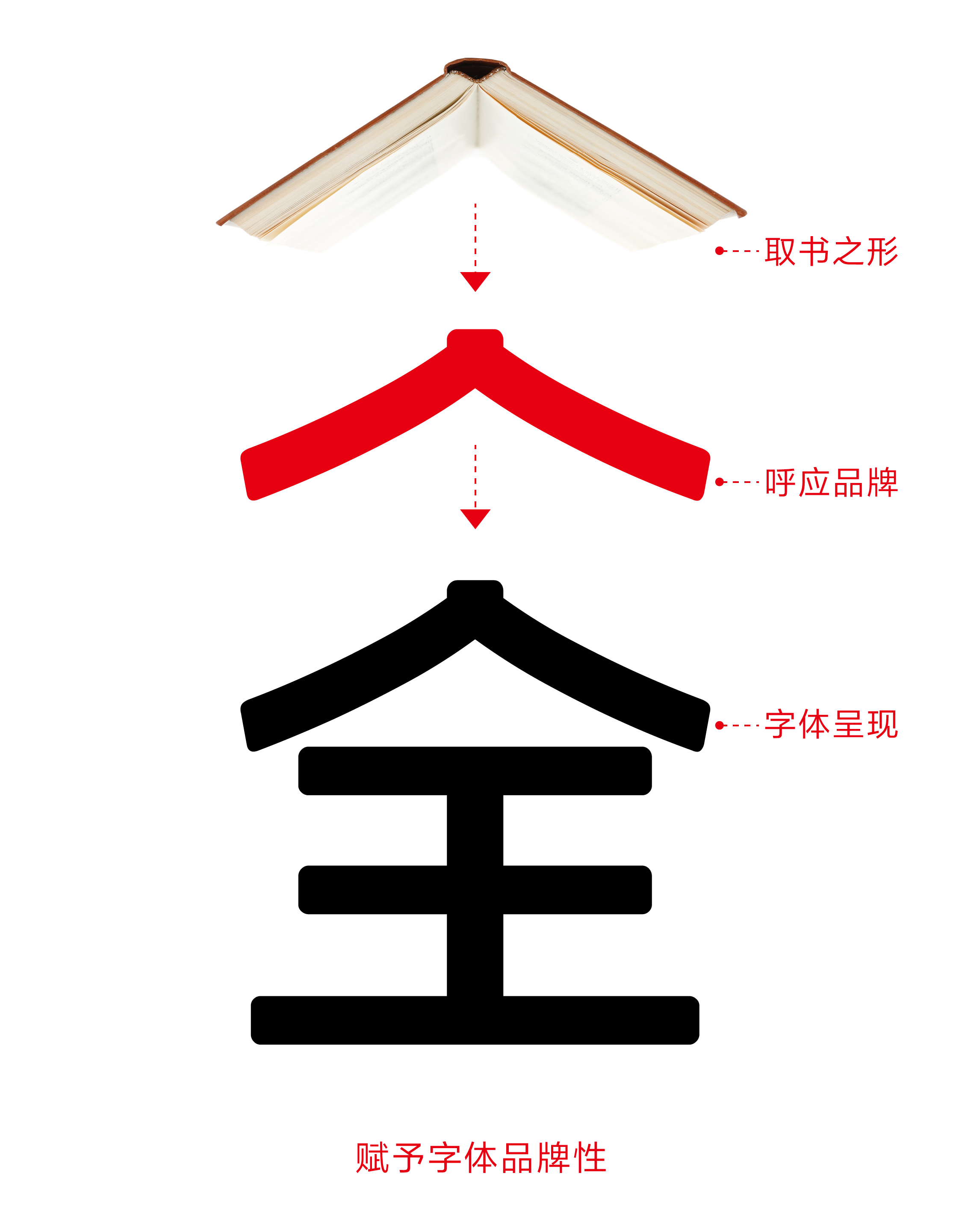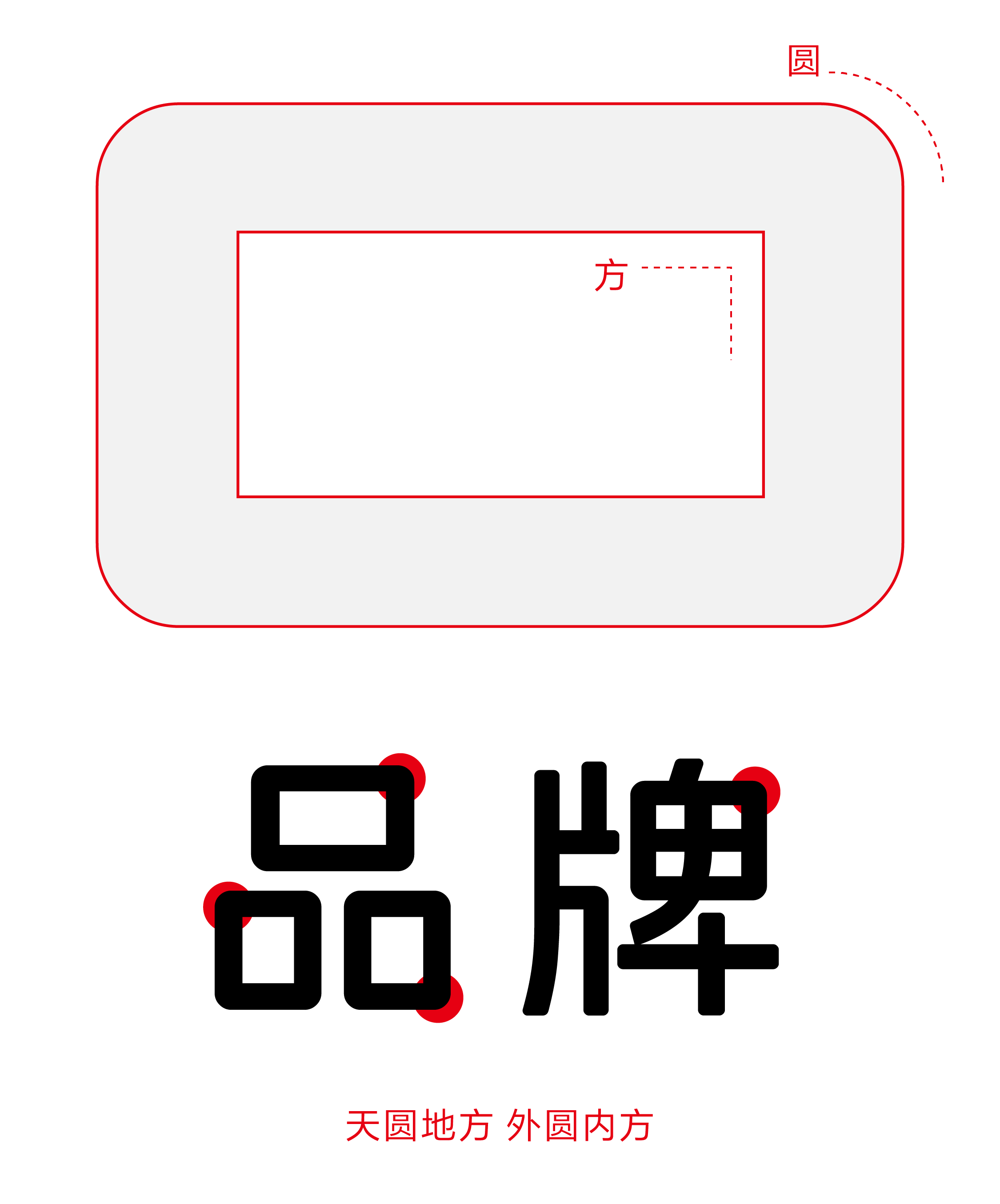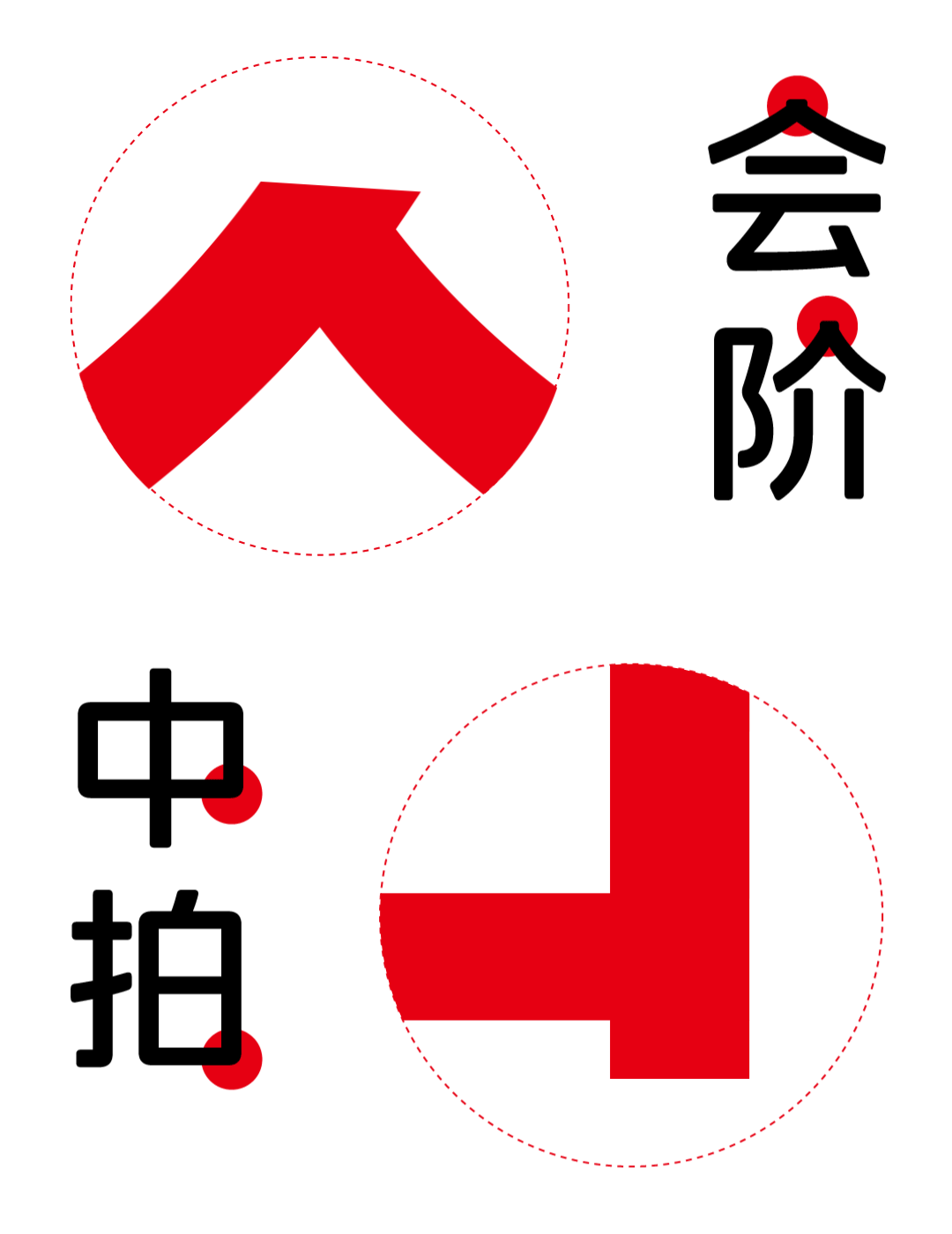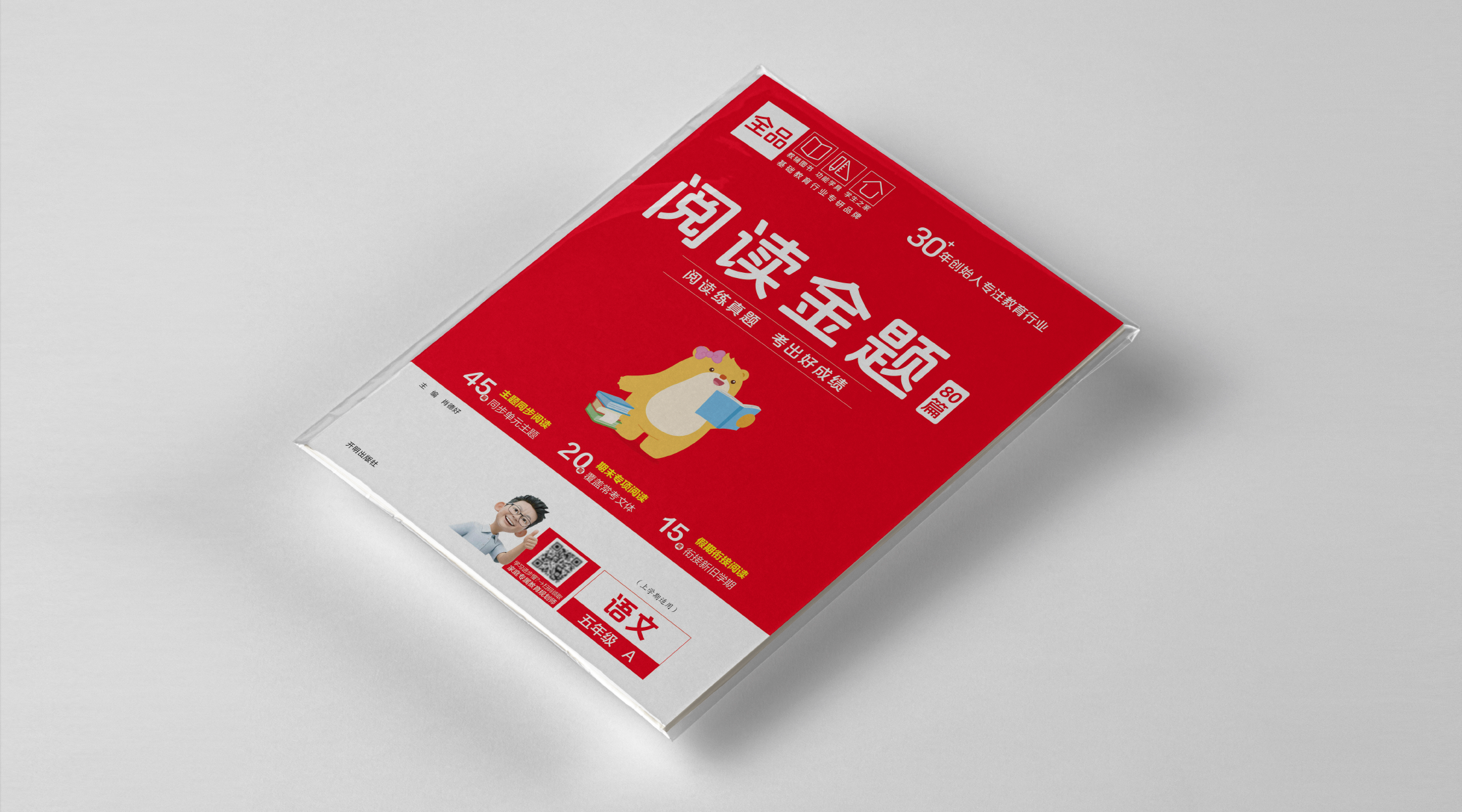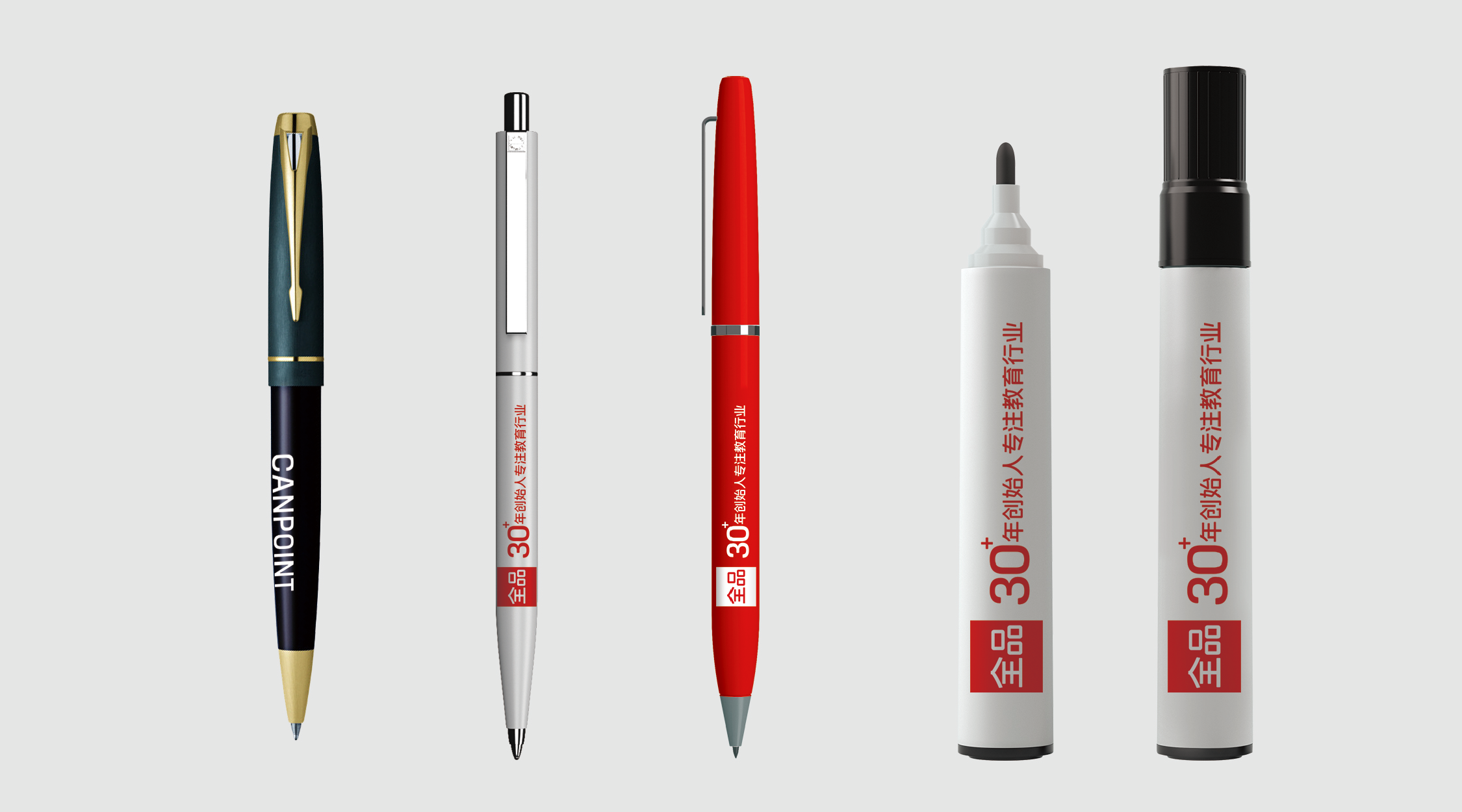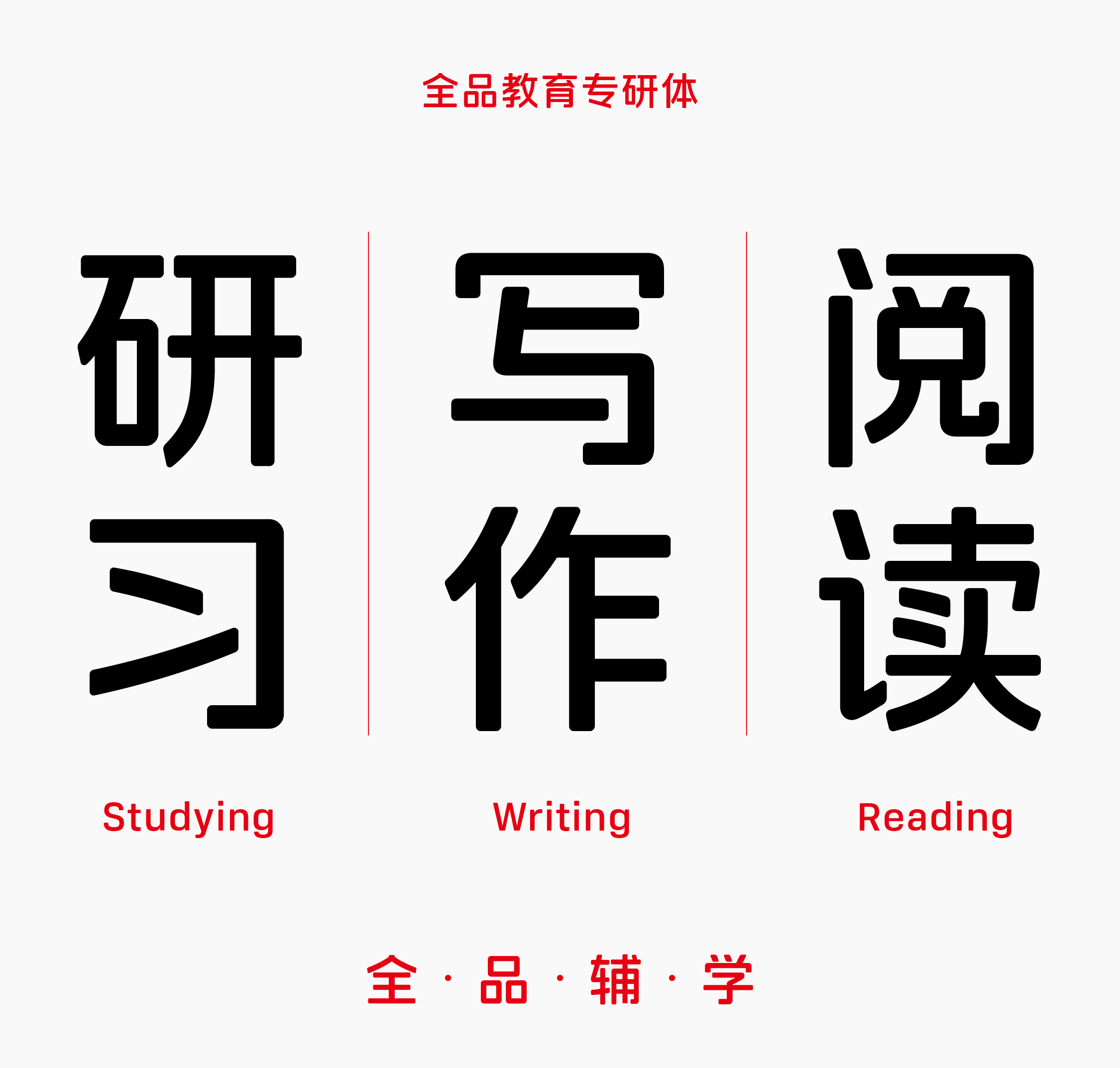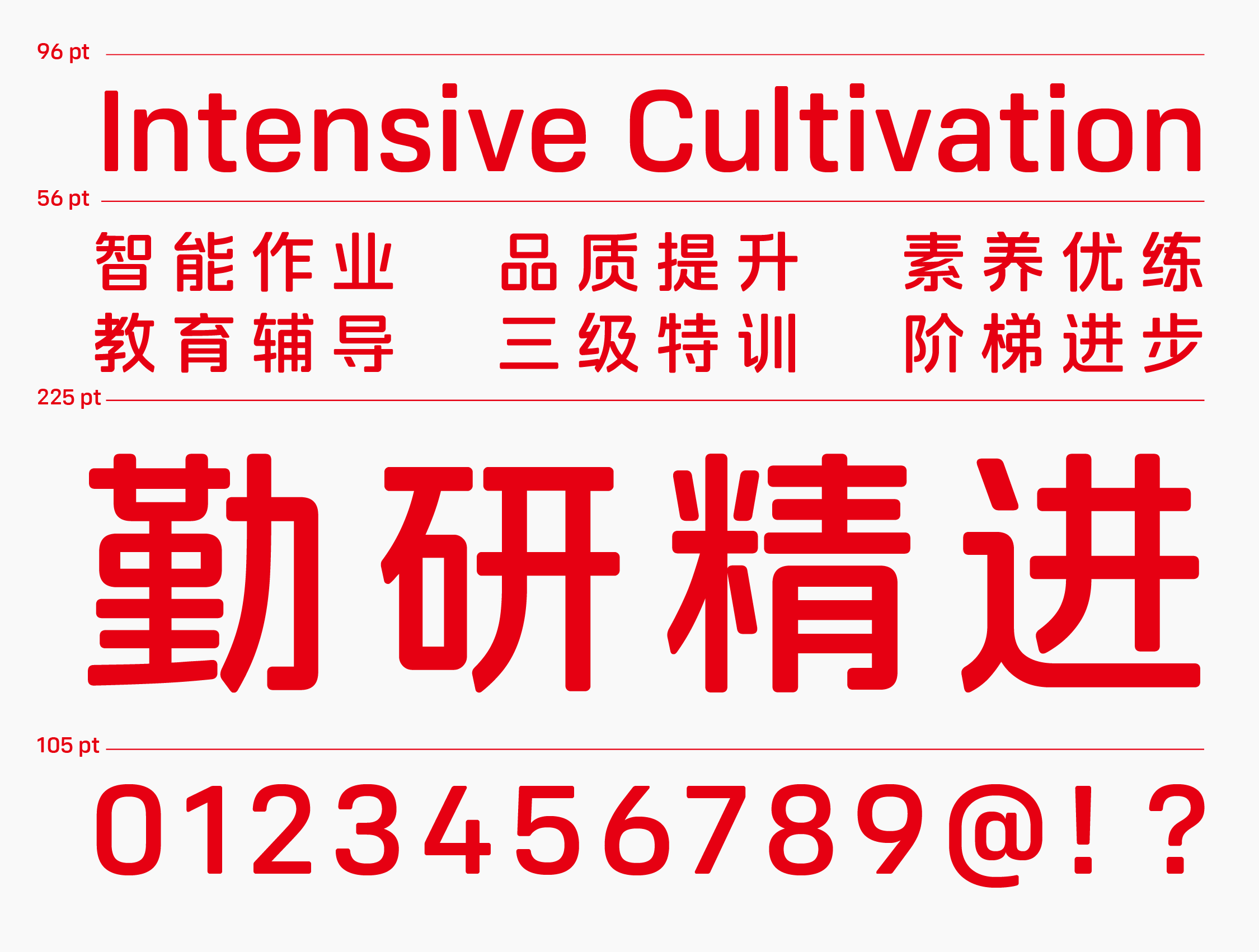
在中华文化源远流长的文脉中,“汉印”的存在不止于权威,更是美学的浓缩展现,其“天圆地方”的设计理念,将中华传统美学完美展现,成为传统美学的重要符号。正是源于对汉印精神的延续与再激活,全品联合方正字库推出独家定制字体“全品教育专研体”。
全品文教字体以汉印美学为根基,将“天圆地方”的哲学智慧与“外圆内方”的处世之道融入字体设计。篆刻艺术的圆融轮廓与方正骨架,凝练为品牌视觉的双重语言:外廓圆润柔和,象征全品教育生态的包容与开放;内角方正严谨,承载着创始人33年来深耕行业的专业与坚守。这一设计哲学既承袭汉代官印“平正端方”的精神内核,亦与基础教育“规圆矩方”的育人理念深度共鸣。
本次独家定制字体项目中,方正字库设计团队紧扣“外圆内方”构字精髓,从汉印中提炼两大核心基因。
“全”字顶部的“人”字部首,以书籍倒扣的意象造型呼应全品的图书主业,通过倒圆的设计手法,呼应全品“以人为本”的服务理念,赋予品牌温润亲和力。
“品”字模块融合“天圆地方”哲学,外部圆润边界象征教育生态的开放性,内部方正结构象征知识体系的严谨性,实现传统美学与现代教育场景的有机衔接。
https://cdn1.foundertype.com/Public/Uploads/img/customcase_attach_20260210100453_9072.png为精准适配现代化教育需求,设计团队从三大维度重构字体功能。
通过结构对称性强化与笔画曲线调整,在确保字体风格统一性的同时,强化基础教育场景所需的规范性。
字体骨架的均衡布局与笔画间的精确比例,既延续了汉印"平正端方"的视觉传统,又与现代教育场景的秩序需求深度契合,使品牌标识在各类应用环境中保持专业严谨的视觉表达。
以倒圆的设计手法巧妙地融合了传统与现代的美学理念,同时,对字体进行了曲线流畅的统一的处理。
通过这样巧妙的字体设计手法,既延续教辅批改的书写记忆,又以现代设计语言重构品牌亲和力。
采取笔画减省策略,通过对字体切⻆和收笔形态的统一处理,确保字体的专业度与一致性,赋予字体简约科技感。
这种精细化处理使字体适配从纸质阅读到线上浏览的全场景需求,保障信息传递的清晰度。
通过专业处理,让字体从单一识别符号转为品牌理念的具象体现,传承品牌原生的文化气质的同时,在视觉语言上完成了面向未来的优化更新。
字体设计不仅是造型问题,更是品牌共识的重构。全品文教在长期教育内容与服务的沉淀中,形成了“全心全意、品质为真”的品牌理念,这一次全品联合方正推出独家定制字体,是品牌与字体设计对同一价值观的共同书写。
从汉印的“形”,到教育的“意”,再到当代字形的“态”,全品与方正字库通过极具美感的专业字体设计,为品牌注入清晰而温润的视觉语言,也为教育行业的视觉表达建立可持续的设计参考,在汉字的方寸之间,发现教育的温度与美。